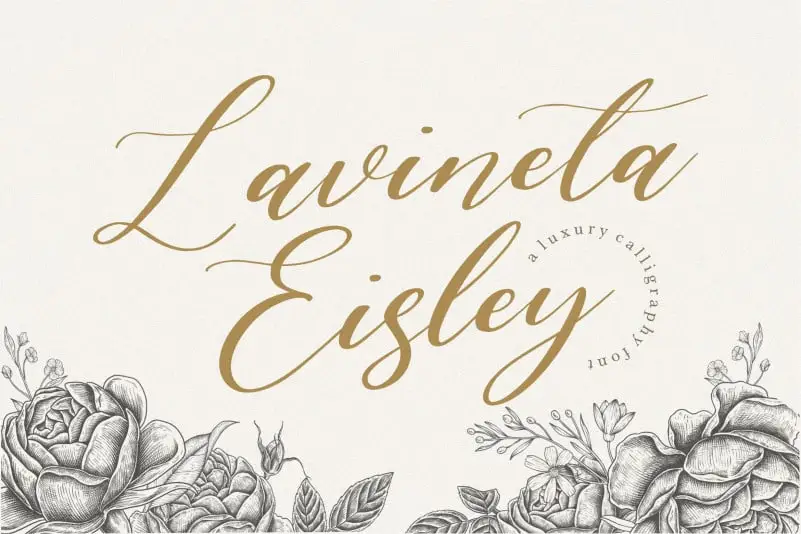
Lavineta Eisley Luxury Calligraphy Font – Download Grátis
A fonte Lavineta Eisley Luxury Calligraphy é perfeita para criar designs únicos e elegantes que se destacam em qualquer projeto. Suas linhas delicadas e acabamento suave fazem dela uma escolha ideal tanto para ambientes de marca ou produto, quanto para elementos como capa de revistas, mídias sociais, cartões de aniversário ou mesmo apenas para decorar o fundo de um texto. Ideal para quem busca expressar uma mensagem com estilo e sofisticação, essa fonte é perfeita para atender a diferentes necessidades gráficas que exigem um toque especial e elegante. Com Lavineta Eisley Luxury Calligraphy, transforme seus projetos em verdadeiros estandartes de criatividade e sofisticação.